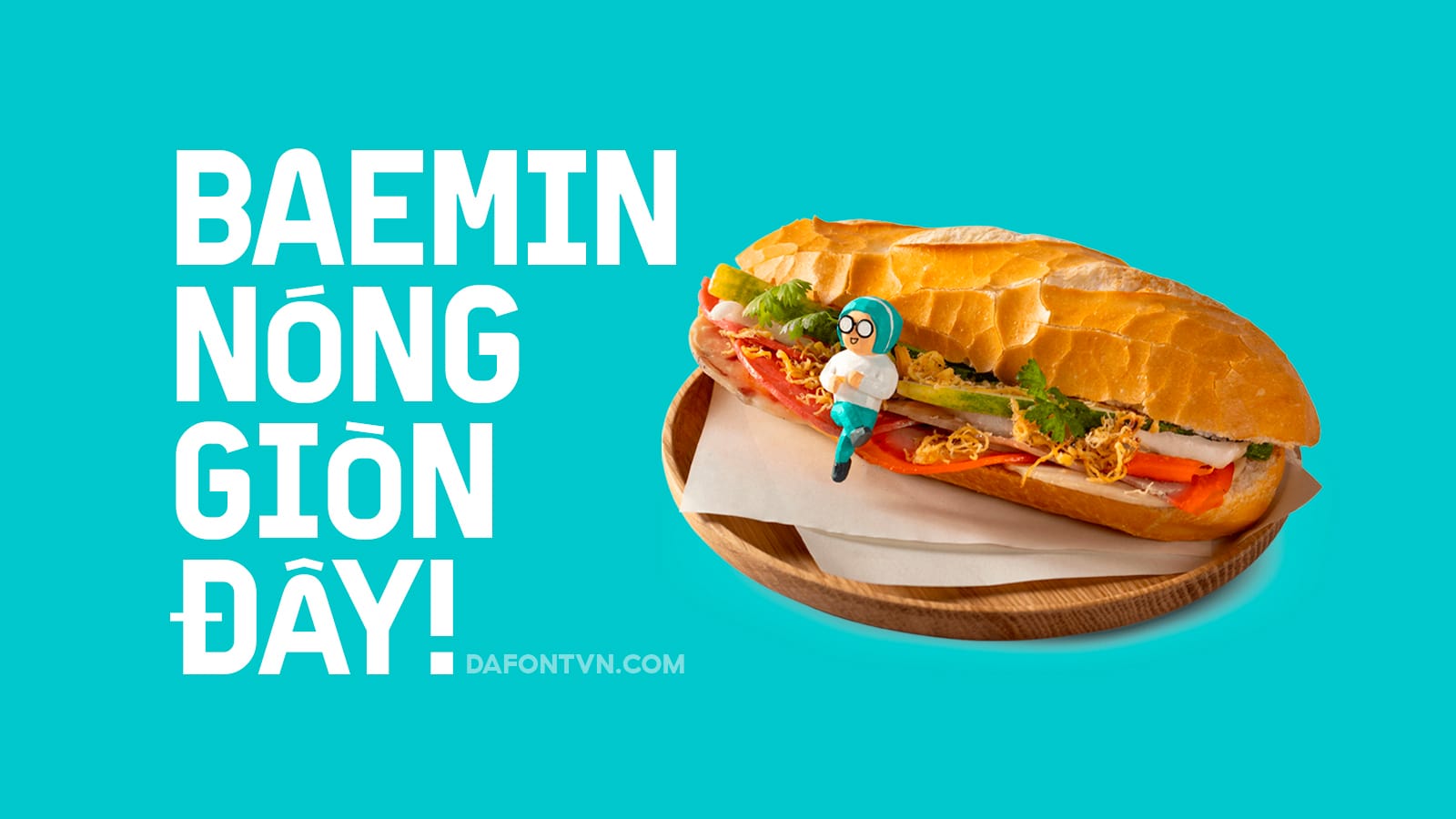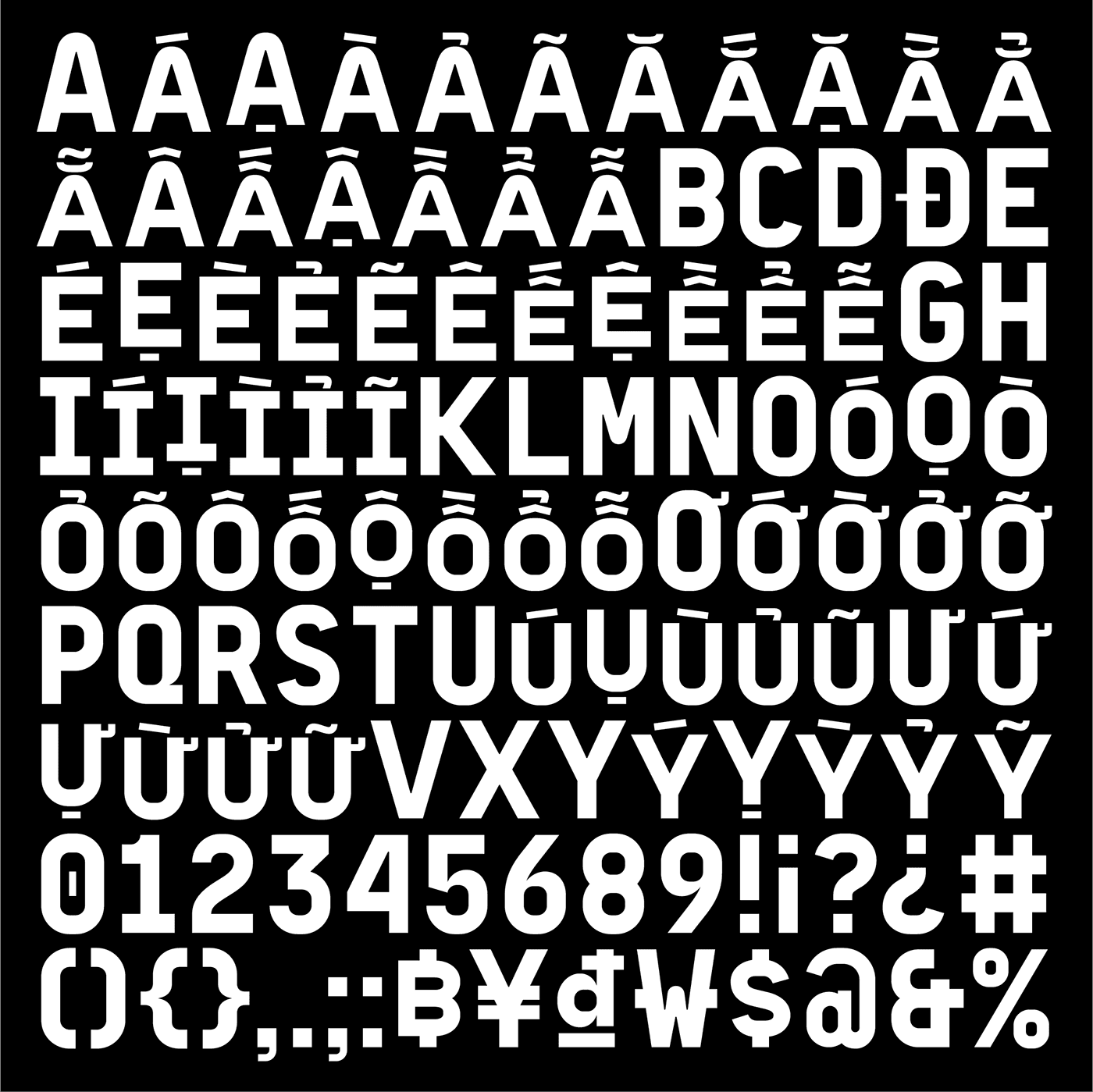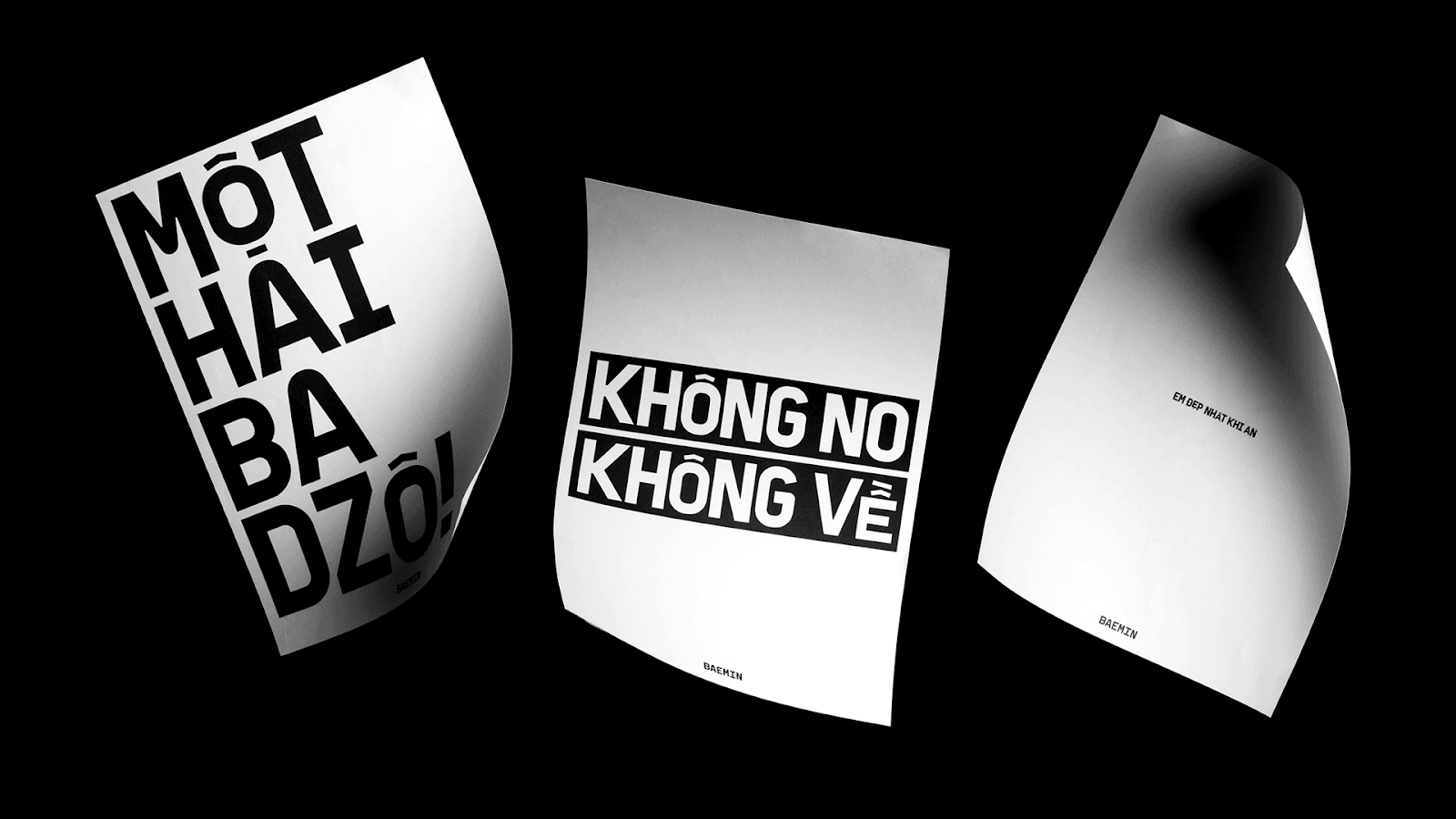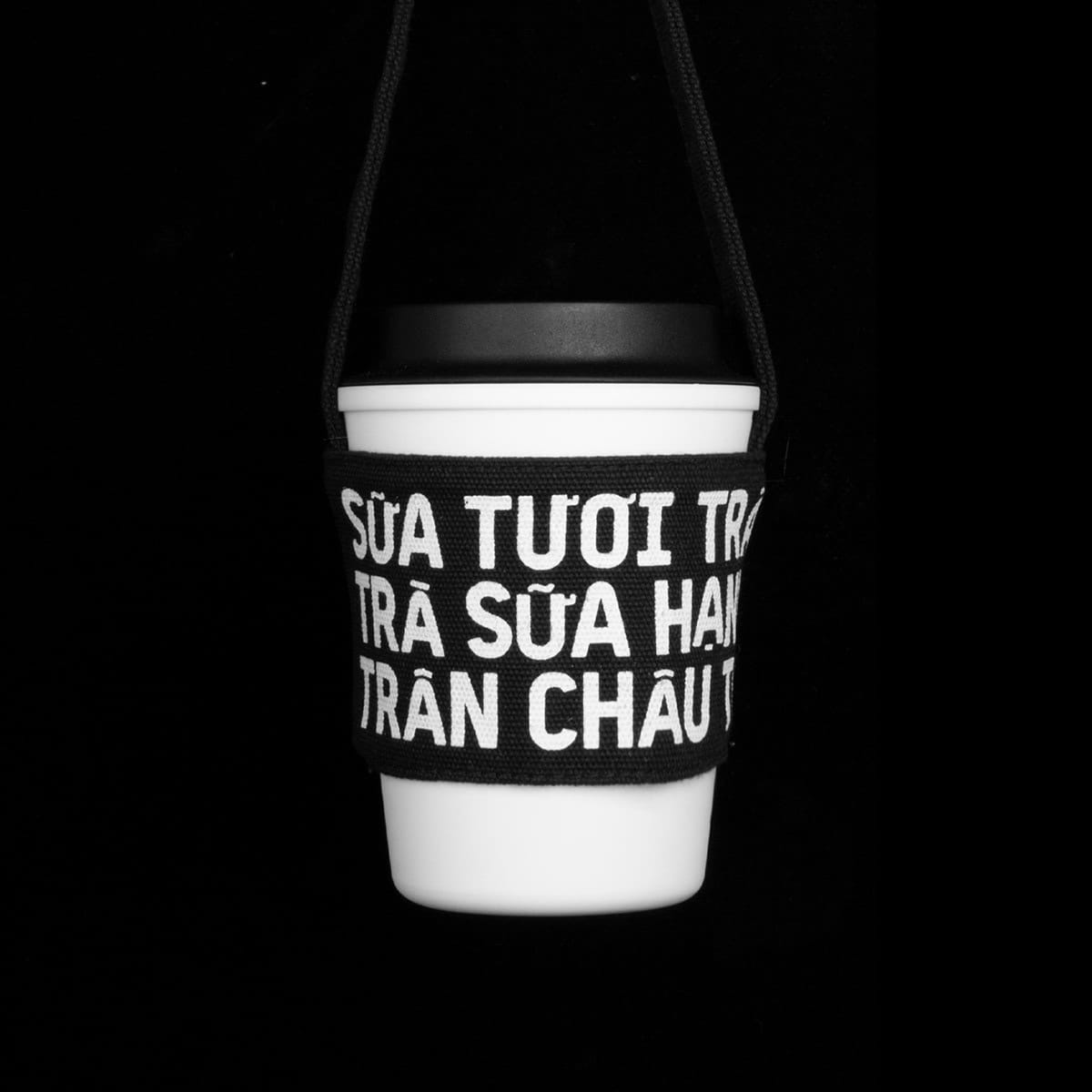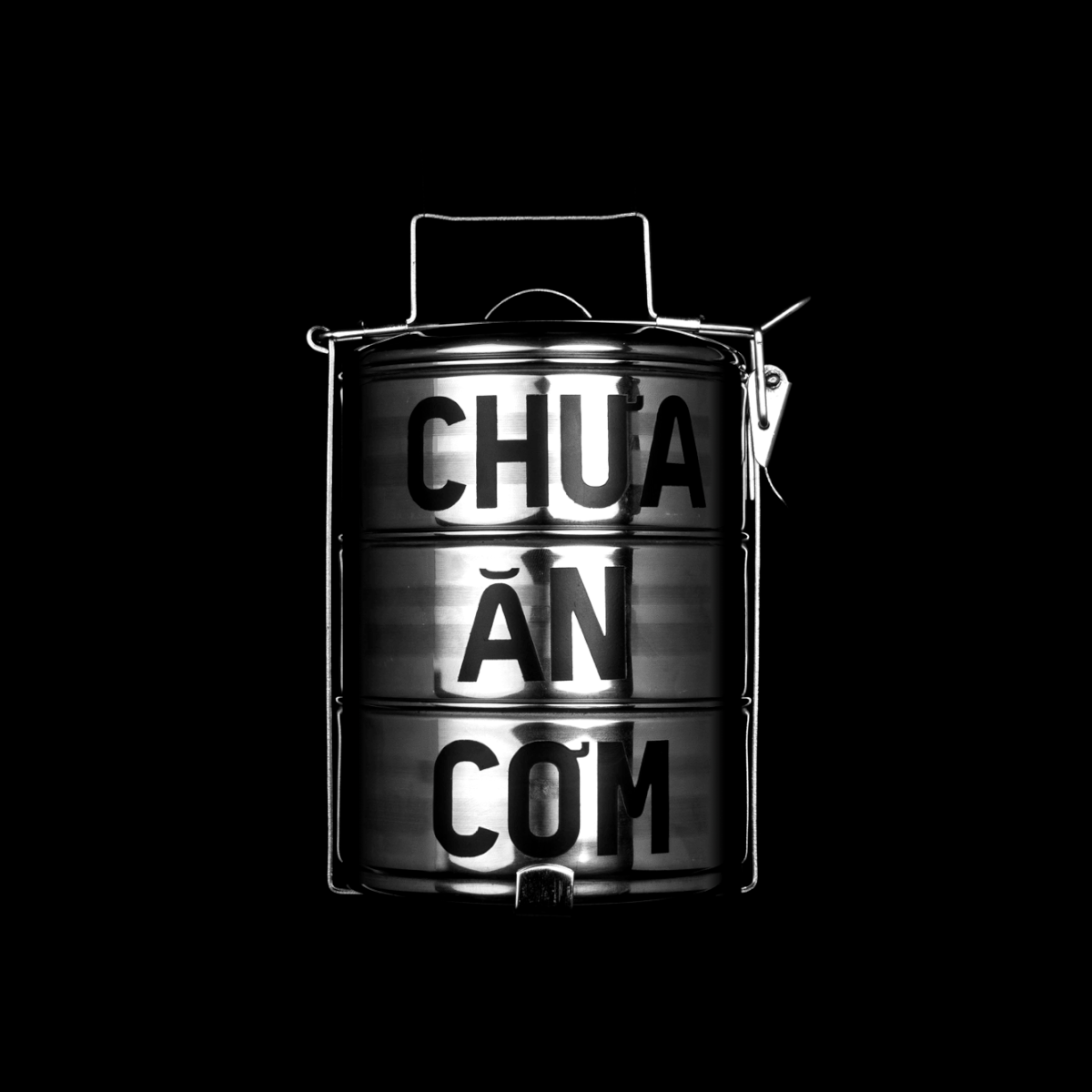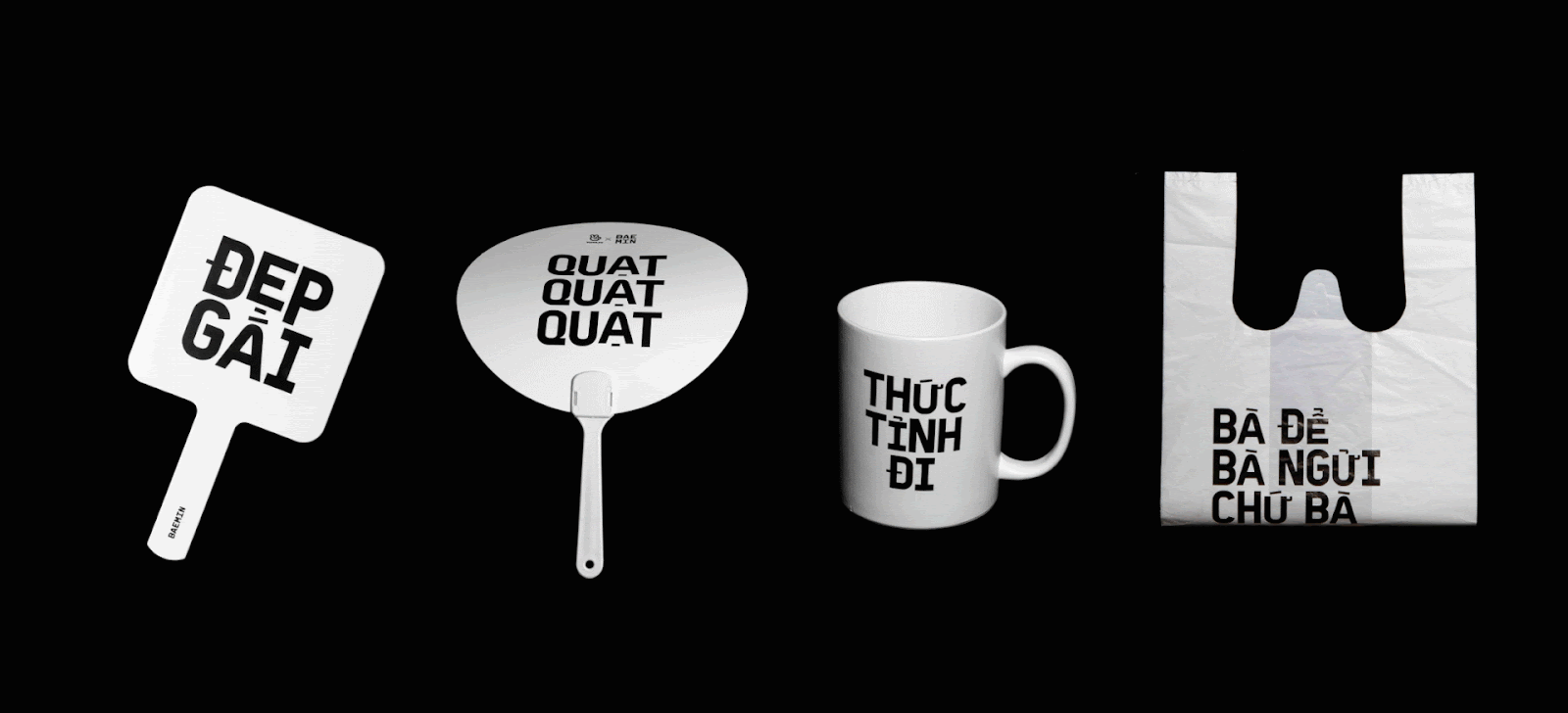
Font BAEMIN – BAEMIN Nóng giòn đây!
Đây là font chữ độc quyền thiết kế dành riêng cho BAEMIN Food, một font chữ khá ấn tượng với các dấu và chữ mới lạ.
Font chữ BAEMIN có tên là BM Daniel là kiểu chữ hiển thị tùy chỉnh được phát triển đặc biệt cho Baemin Việt Nam, thương hiệu giao đồ ăn lớn nhất Việt Nam.
BM Daniel được thiết kế với bảng chữ cái tiếng Việt. Để thích ứng với một cách thật cá tính, kiểu chữ được thiết kế đặc biệt với nét đậm, tròn và cỡ to nhỏ, kiểu chữ đã trở thành đặc điểm nhận dạng trực quan cho thương hiệu Baemin.